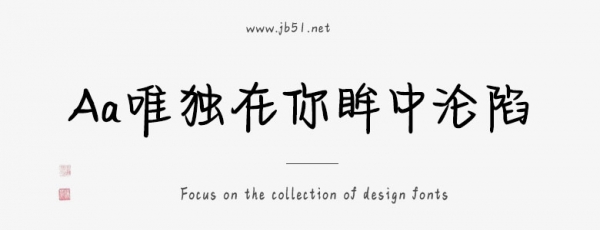
Aa唯獨(dú)在你眸中淪陷,字體筆觸略細(xì),具有很好的視覺(jué)感,適合應(yīng)用于藝術(shù)設(shè)計(jì)、平面宣傳設(shè)計(jì)、網(wǎng)頁(yè)設(shè)計(jì),書(shū)法字帖等領(lǐng)域。有需要的朋友快來(lái)本站下載使用吧。